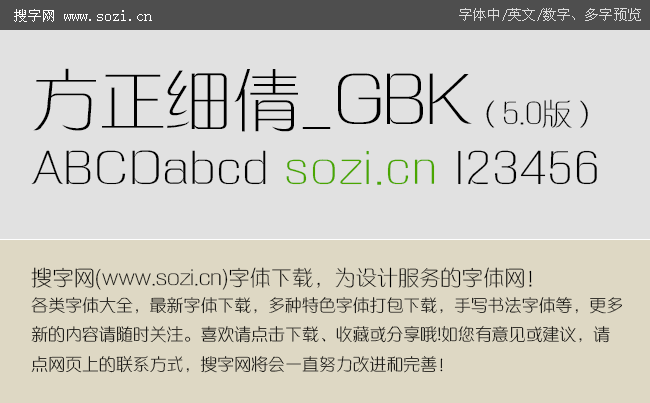
方正細(xì)倩-GBK
搜字網(wǎng)給大家提供一款方正細(xì)倩-GBK下載。GBK標(biāo)準(zhǔn)收錄漢字更全,細(xì)倩體親切、幽雅、柔美和華麗,纖細(xì)的筆致顯得文靜、清雅,襯上了柔軟的弧線,更顯輕盈活潑。適用于個(gè)人用品、化裝品、食品、家居廣告宣傳使用環(huán)境。